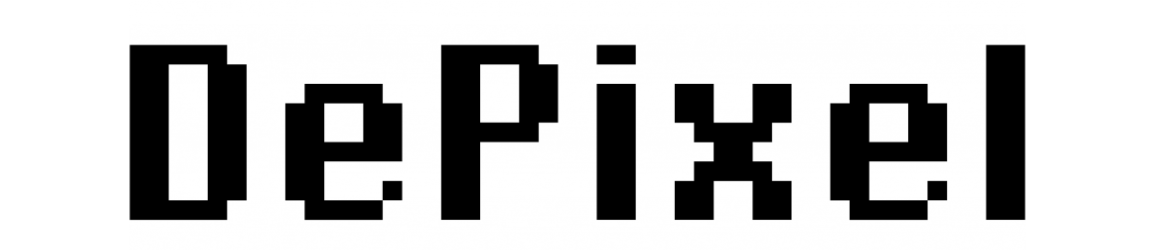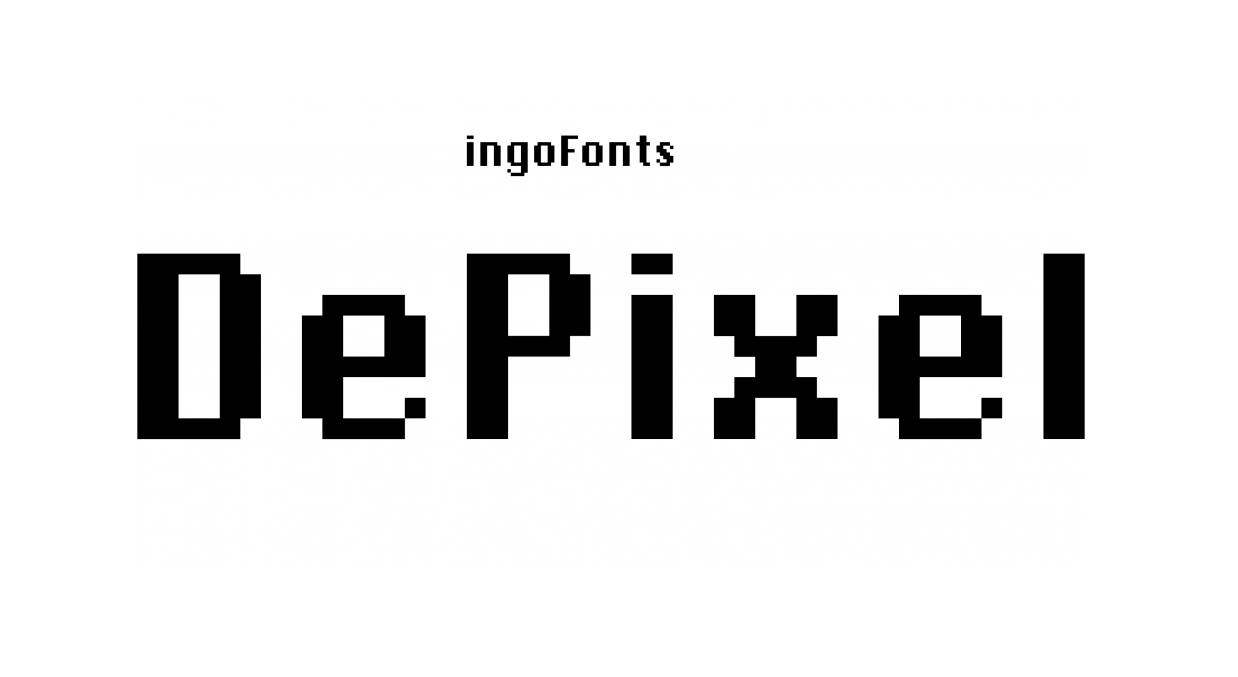
Descubra a DePixel Font Family, uma nova família de fontes pixel art desenvolvida pelo designer Ingo Zimmerman e publicada pela ingoFonts. Inspirada nas famosas fontes monitor do Apple, como “Geneva” e “Chicago”, essa família de pixels apresenta um design que imita os pixels individuais configurados em letras. A DePixel é uma criação atraente para quem busca algo diferente no mundo das fontes digitais. Ela simula a configuração dos pixels para criar texto, o que resulta em uma fonte reconhecível mesmo quando diminuída em tamanho. Esta característica permite que você utilize essa fonte sem preocupações, independente do tamanho da sua letra – seja grande ou pequeno. Com suas características de pixel art distintas e arredondadas, a DePixel oferece um design único e envolvente. Seja para títulos chamativos ou textos detalhados, essa família de fontes pixelada mantém seu brilho característico. Experimente incorporar a DePixel na sua próxima peça gráfica digital e deixe marcar as impressões de sua arte com um toque nostálgico do tempo dos computadores de pixels.